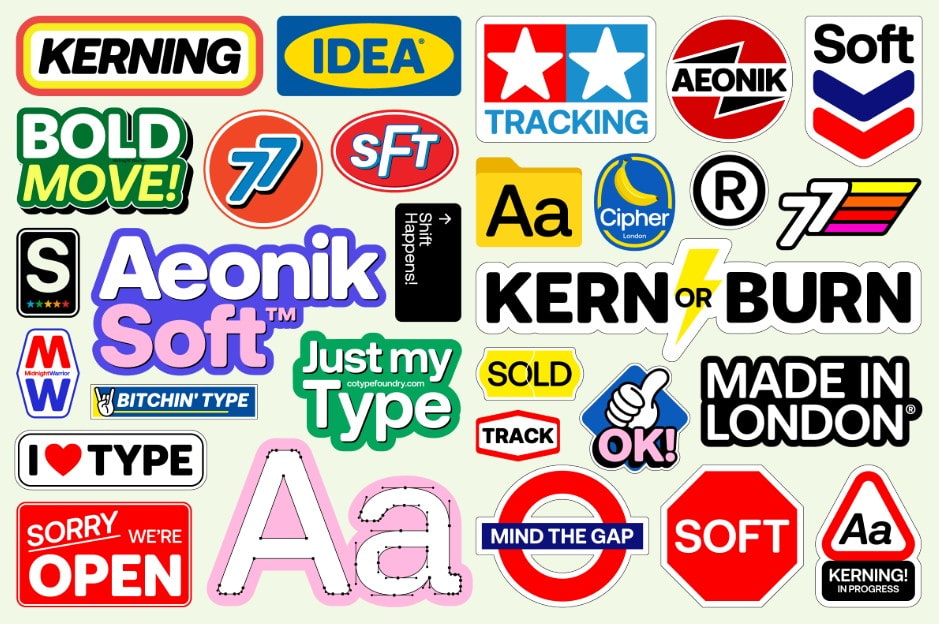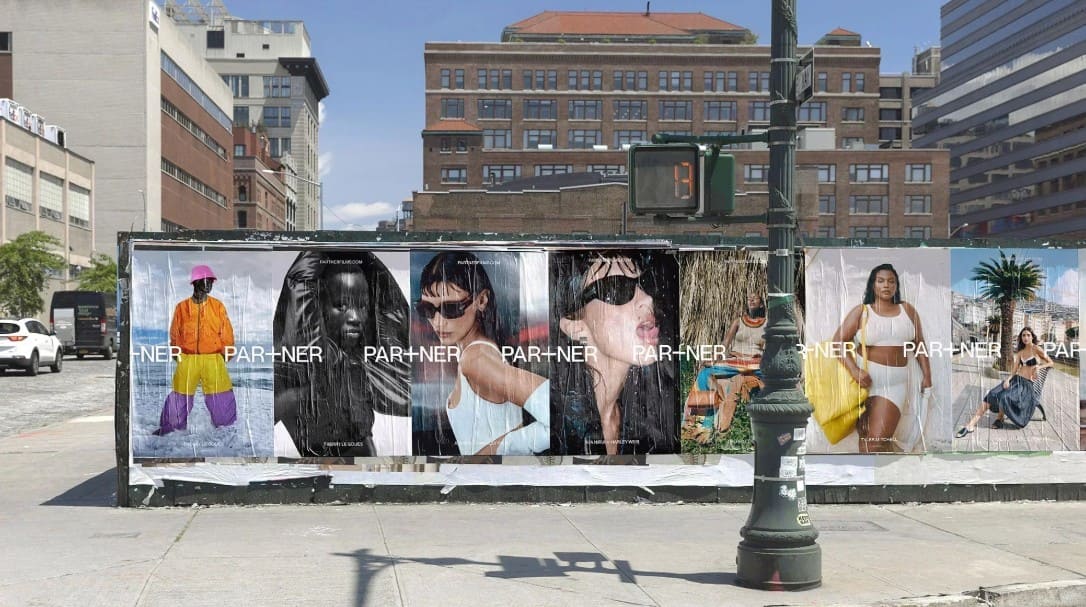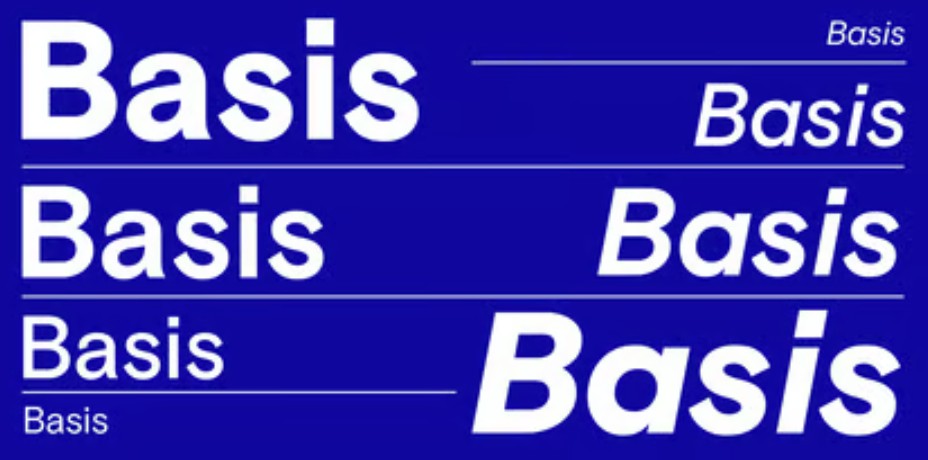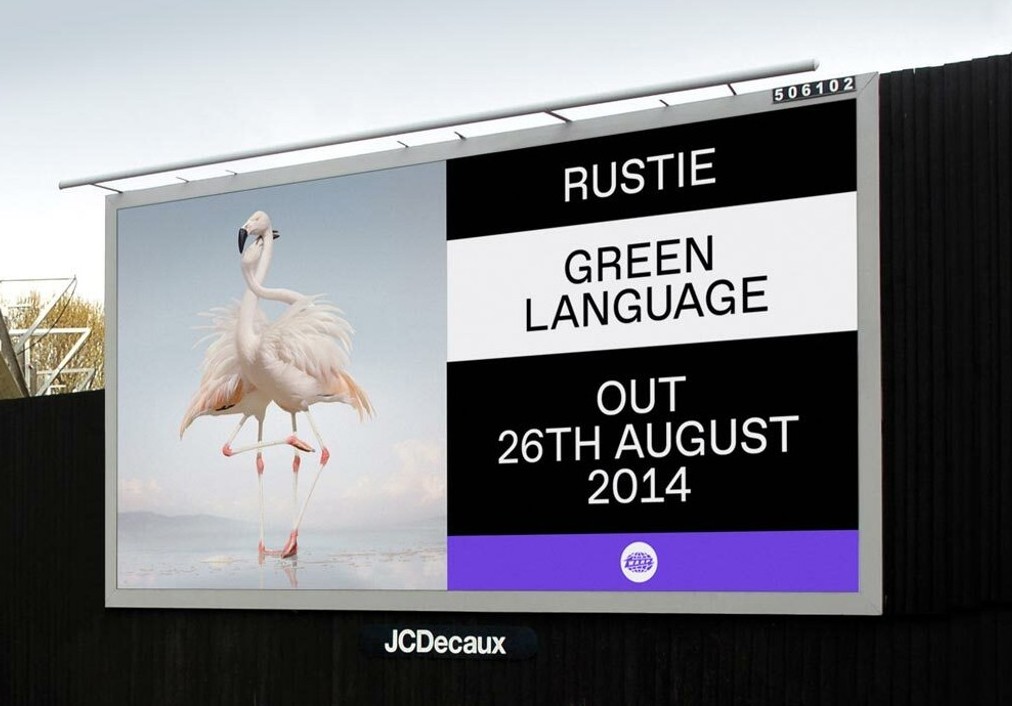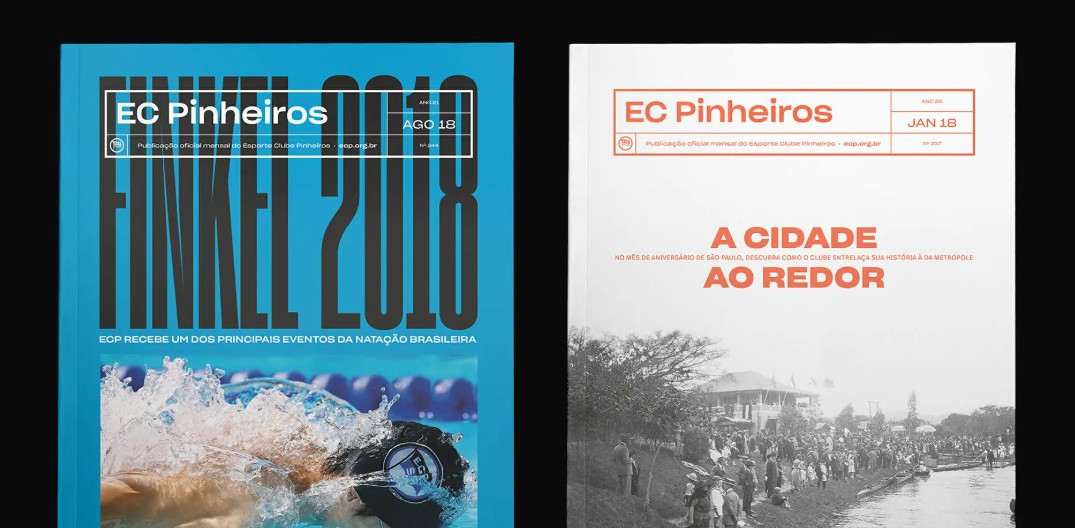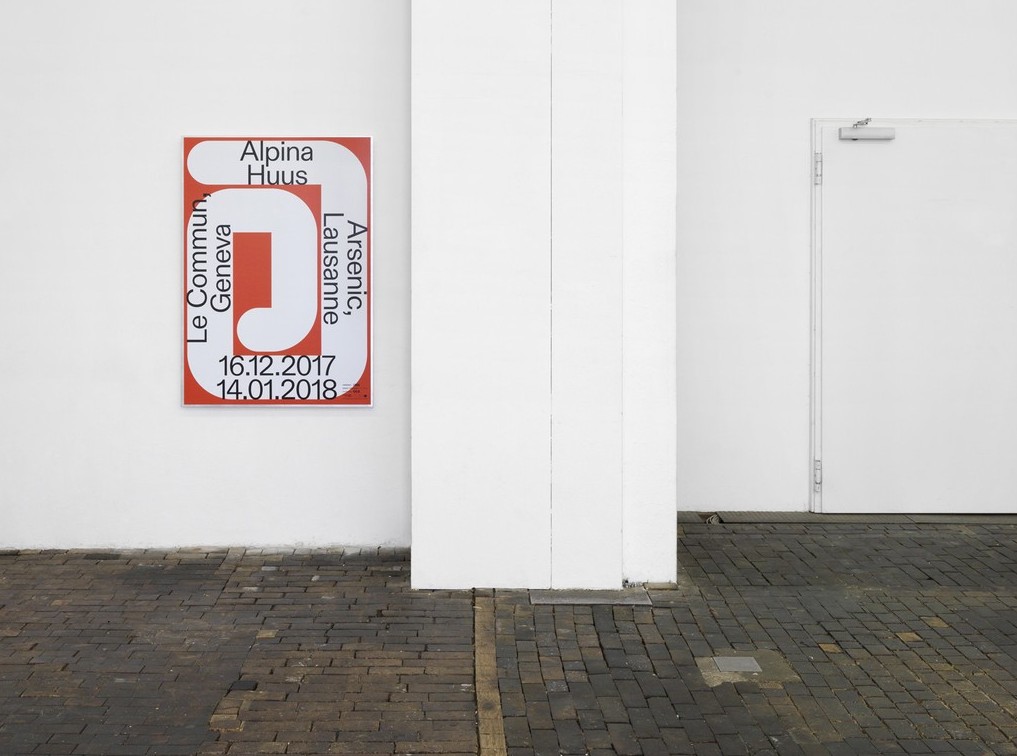
50 font chữ dự đoán sẽ “lên ngôi” trong thiết kế năm 2026
Typography luôn là yếu tố quan trọng tạo nên cá tính cho một thiết kế. Năm 2026 hứa hẹn mang đến nhiều xu hướng font chữ mới từ tối giản hiện đại đến phong cách retro sáng tạo. Danh sách này sẽ giúp bạn khám phá những kiểu chữ được dự đoán sẽ xuất hiện nhiều nhất trong các dự án thiết kế.
Bước sang năm 2026, xu hướng typography tiếp tục chịu ảnh hưởng bởi nhiều yếu tố như sự phát triển của công nghệ font biến đổi (variable fonts), nhu cầu thiết kế đa nền tảng, cũng như sự quay trở lại của các phong cách chữ cổ điển được tái diễn giải theo tinh thần hiện đại. Những kiểu chữ grotesque và neo-grotesque vẫn giữ vị trí trung tâm trong thiết kế đương đại vì khả năng cân bằng giữa tính trung lập, tính linh hoạt và tính thẩm mỹ. Đồng thời, các nhà thiết kế cũng tìm kiếm những kiểu chữ có cá tính rõ ràng để tạo nên bản sắc riêng cho thương hiệu và sản phẩm.
Bài viết này giới thiệu một số kiểu chữ tiêu biểu đang được giới thiết kế quan tâm và nhiều khả năng sẽ tiếp tục được ưa chuộng trong năm 2026. Những kiểu chữ này không chỉ nổi bật về mặt thẩm mỹ mà còn thể hiện sự tinh tế trong cấu trúc, khả năng ứng dụng linh hoạt và sự thích nghi với môi trường thiết kế hiện đại.
1. GT America của Grilli Type
GT America là một trong những kiểu chữ nổi bật nhất trong thế giới typography hiện đại. Được thiết kế bởi Noël Leu cùng với Seb McLauchlan, kiểu chữ này ra đời với tham vọng kết nối hai truyền thống typographic quan trọng: trường phái Gothic Mỹ thế kỷ 19 và phong cách Neo-Grotesk châu Âu thế kỷ 20. Hai dòng ảnh hưởng này vốn có những đặc điểm khác nhau về cấu trúc và thẩm mỹ nhưng GT America đã thành công trong việc chắt lọc những yếu tố tinh túy nhất từ cả hai để tạo nên một kiểu chữ vừa quen thuộc vừa mới mẻ.
Điểm đặc biệt của GT America nằm ở tính linh hoạt đáng kinh ngạc của nó. Bộ font này bao gồm tới 84 kiểu chữ khác nhau, từ những trọng lượng mảnh nhẹ cho đến những biến thể đậm mạnh mẽ. Sự đa dạng này cho phép các nhà thiết kế sử dụng GT America trong nhiều ngữ cảnh khác nhau, từ hệ thống nhận diện thương hiệu doanh nghiệp đến thiết kế biên tập và giao diện kỹ thuật số.
Một yếu tố khác khiến GT America trở nên hấp dẫn là sự cân bằng giữa tính hiện đại và tính lịch sử. Những đặc điểm của Gothic Mỹ mang lại cảm giác chắc chắn và thực dụng, trong khi ảnh hưởng của Neo-Grotesk châu Âu giúp kiểu chữ này trở nên tinh gọn và hiện đại hơn. Sự kết hợp này khiến GT America trở thành lựa chọn lý tưởng cho các thương hiệu muốn truyền tải hình ảnh chuyên nghiệp nhưng vẫn mang tính cá nhân.
Ngoài ra, GT America còn được mở rộng với các bộ ký tự viết tay phong phú do Tania Chacana phát triển. Những phần mở rộng này giúp kiểu chữ có khả năng hỗ trợ nhiều ngôn ngữ và hệ thống chữ viết khác nhau, làm tăng đáng kể tính ứng dụng trong môi trường thiết kế toàn cầu.
2. Söhne của Klim Type Foundry
Söhne là một kiểu chữ được thiết kế bởi Kris Sowersby của Klim Type Foundry. Kiểu chữ này lấy cảm hứng mạnh mẽ từ Akzidenz-Grotesk, một trong những kiểu chữ grotesque mang tính biểu tượng của thế kỷ 20. Tuy nhiên, thay vì chỉ đơn thuần tái hiện lại thiết kế cổ điển, Sowersby đã tiếp cận dự án này theo hướng tinh tế hơn, kết hợp các yếu tố lịch sử với cảm quan thẩm mỹ hiện đại.
Một nguồn cảm hứng quan trọng của Söhne là Standard Medium, kiểu chữ từng được sử dụng rộng rãi trong hệ thống biển báo tàu điện ngầm tại New York. Chính vì vậy, Söhne mang trong mình cảm giác mạnh mẽ, rõ ràng và dễ đọc, đồng thời gợi lên bầu không khí đô thị đặc trưng.
Tuy vậy, Söhne không phải là một bản phục dựng đơn giản. Sowersby đã điều chỉnh tỷ lệ chữ, độ dày nét và các chi tiết nhỏ để tạo ra một kiểu chữ mang tính đương đại. Kết quả là một kiểu chữ vừa có vẻ cổ điển vừa mang hơi thở mới, phù hợp với nhu cầu thiết kế ngày nay.
Một điểm đáng chú ý của Söhne là cách nó được xây dựng từ trọng lượng semibold trở lên. Điều này tạo ra cảm giác chắc chắn và tự tin cho kiểu chữ, khiến nó đặc biệt phù hợp với thiết kế thương hiệu và tiêu đề. Ngoài ra, bộ font còn bao gồm các biến thể thu gọn, mở rộng và đơn khoảng cách, giúp nó thích nghi với nhiều loại bố cục khác nhau.
Nhờ sự kết hợp giữa lịch sử typographic và tinh thần hiện đại, Söhne đã nhanh chóng trở thành một trong những kiểu chữ được các nhà thiết kế ưa chuộng trong những năm gần đây.
3. Graphik by Commercial Type
Graphik là một trong những kiểu chữ nổi tiếng nhất của Commercial Type và đã trở thành lựa chọn phổ biến trong nhiều dự án thiết kế biên tập. Được mô tả là một kiểu chữ “vô cùng đơn giản”, Graphik thể hiện rõ triết lý thiết kế tối giản nhưng hiệu quả.
Kiểu chữ này là sự kết hợp giữa hai truyền thống typographic: sự tròn trịa hình học của các sans-serif hiện đại và cấu trúc của grotesk châu Âu. Sự kết hợp này giúp Graphik giữ được cảm giác trung tính cần thiết cho thiết kế biên tập, đồng thời vẫn mang nét cá tính riêng.
Một trong những ưu điểm lớn nhất của Graphik là khả năng đọc rất tốt trong các bố cục chật hẹp. Độ tương phản thấp giữa các nét chữ giúp văn bản dễ nhìn hơn trên màn hình cũng như trong in ấn. Khoảng trống bên trong các ký tự được thiết kế rộng rãi, tạo cảm giác thoáng và dễ đọc ngay cả ở kích thước nhỏ.